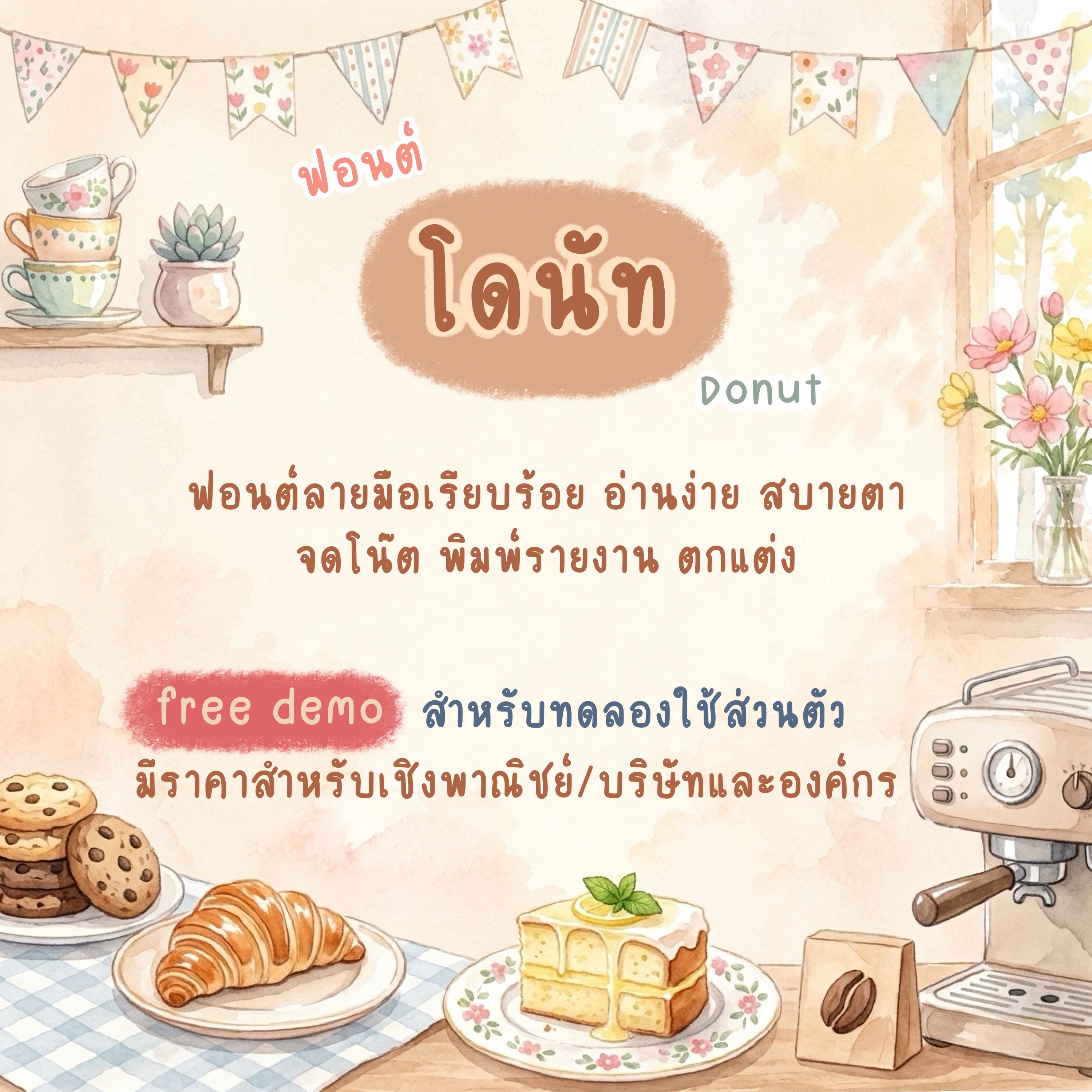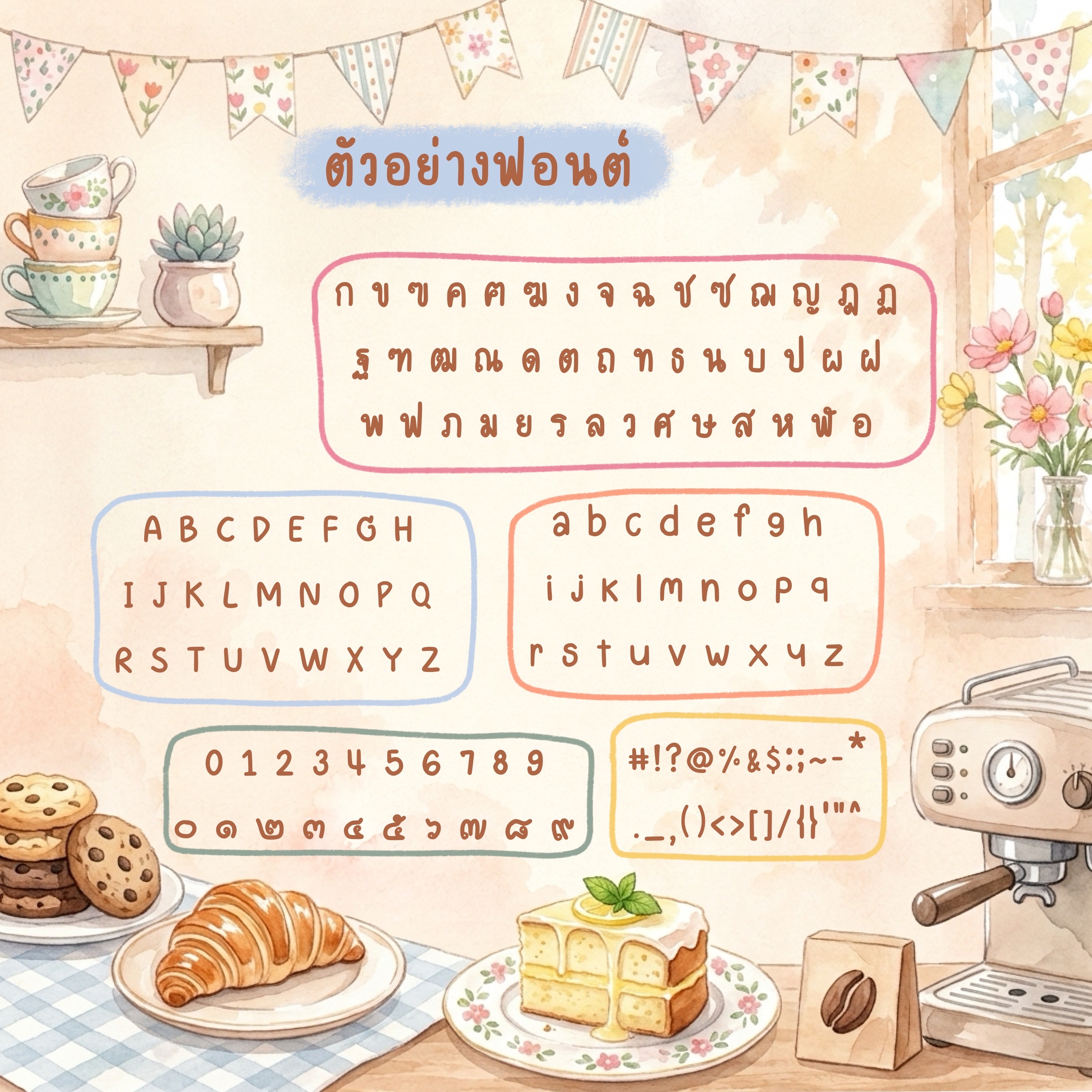
ฟอนต์โมยาชิ (KT-Moyashi)
- ฟอนต์ KanchaEasy ฟอนต์ลายมือแนวน่ารักเรียบร้อย อ่านง่ายสบายตาค่ะ
ฟอนต์โดนัท 🍩
ชื่อฟอนต์ : ยูริ
ฟอนต์ยูริ แนวทางจาก อักษรประกอบภาพยนต์เรื่อง "แก้ว" ปี ๒๕๒๓
ฟอนต์นิทานญี่ปุ่น (EBMonogatari)
ฟอนต์ขี้เกียจบ่น (LBLazytocomplain)
ฟอนต์:ไข่เข็ม(TKKhaikhem)
- ฟอนต์ KanchaEmpty ฟอนต์ลายมือเส้นตัด แนวน่ารักค่ะ